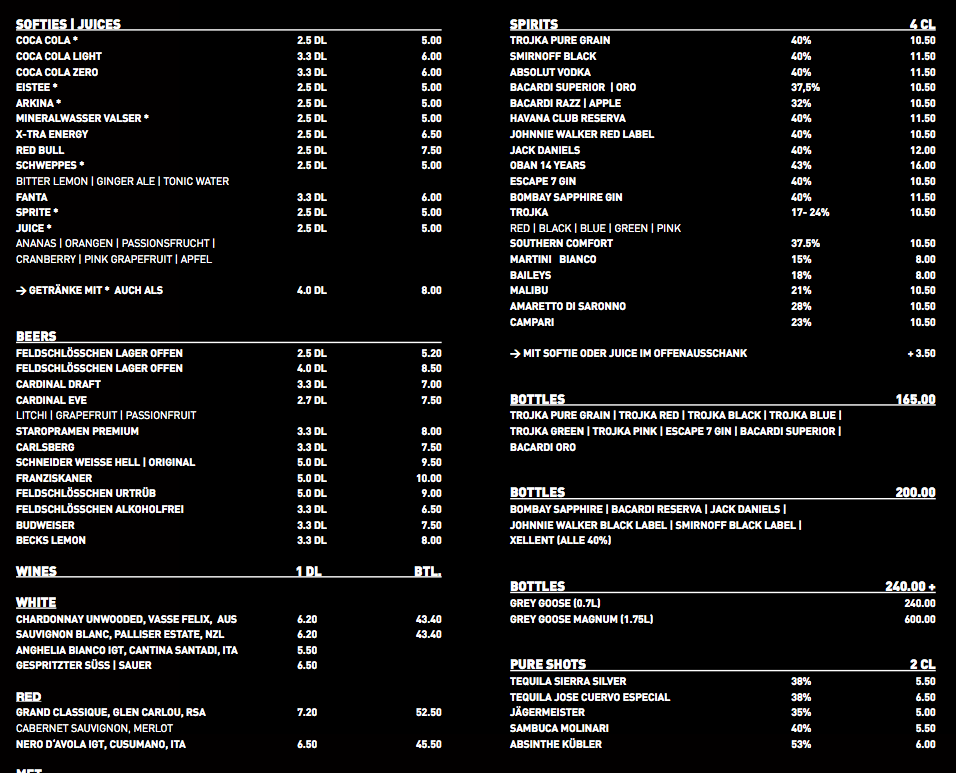
was könnte das denn sein?
weisst du zufällig eine ähnliche schrift die kostenlos ist?
DIN1451 (ohne FF davor)
Aber was ist das ?
... Ansonsten wird Dein Account deaktiviert.
Zu Befehl Herr Direktor.
Immer zu Ihren Diensten.
diese Tafel sieht irgendwie aus wie so eine Steckbuchstabentafel. Und die haben dann immer leicht angerundete Buchstaben. Daher wäre vielleicht die freie Miso von Marten Nettlebladt auch mal in Betracht zu ziehen:
Die Miso ist eine sehr feine Schrift, habe sie selbst schon mehrmals passend eingesetzt und bin sehr zufrieden. Kann den Vorschlag nur unterstützen. Zumal es mal eine schöne Alternative zum ständigen Einsatz der Din ist ...
Wo ist das Problem?
Ein echtes Problem sieht für mich völlig anders aus.
Problematisch ist jedoch, daß mein letzter Beitrag "verschwunden" ist :hammer:
… Problematisch ist jedoch, daß mein letzter Beitrag "verschwunden" ist :hammer:
Zumindest für mich ist das kein Problem. Eventuell hast du dich selbst auf ignorieren gesetzt.